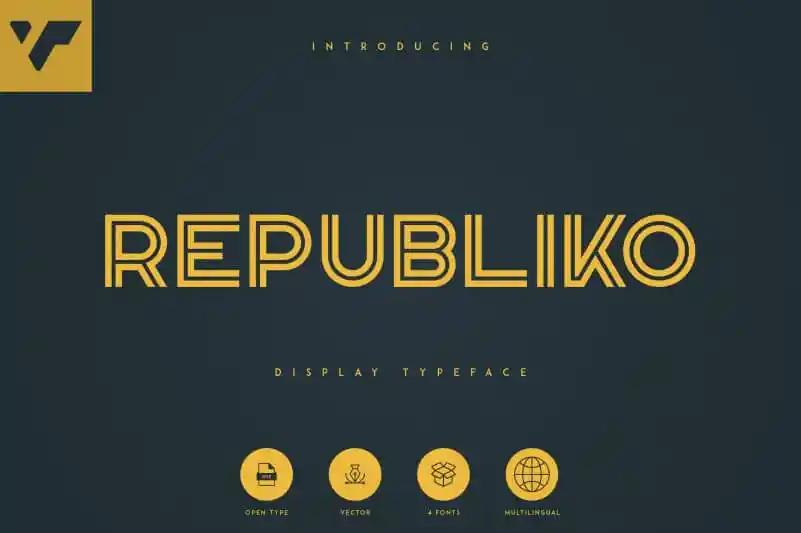
Republiko Display Typeface – 4 Styles – Download Grátis
Republiko Display Typeface é uma tipografia bold e limpa que oferece quatro estilos distintos, com suporte a múltiplas línguas. Ela surge como uma excelente opção para ambientes de design que exigem grande presença visual, seja em grandes tamanhos ou pequenos detalhes. Suavemente minimalista, esta fonte combina elegância e modernidade, tornando-a um recurso valioso tanto para branding quanto para design gráfico, especialmente nas aplicações visuais de produtos digitais. Com seu design contínuo e forte, Republiko Display Typeface é perfeitamente adaptável a diferentes contextos, tornando-se uma excelente escolha para qualquer projeto que busque equilibrar simplicidade e força visual. Seja em sua forma clara ou mais elaborada, esta fonte continua a oferecer visibilidade robusta, sem perder seu caráter distintivo.